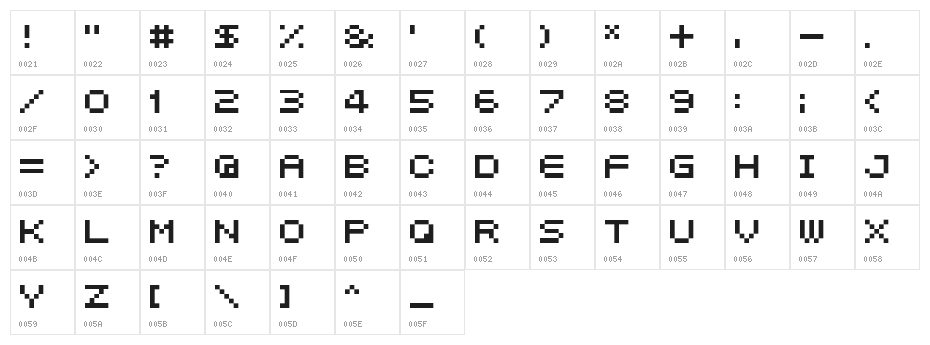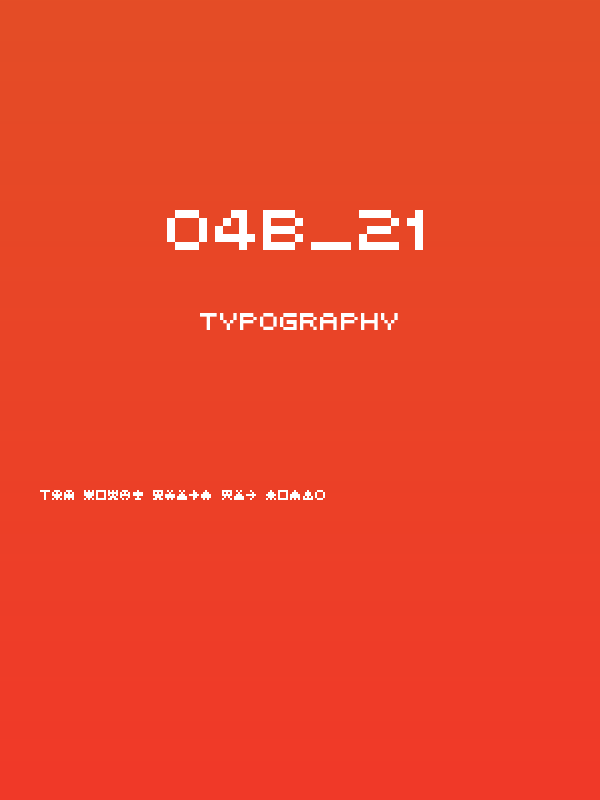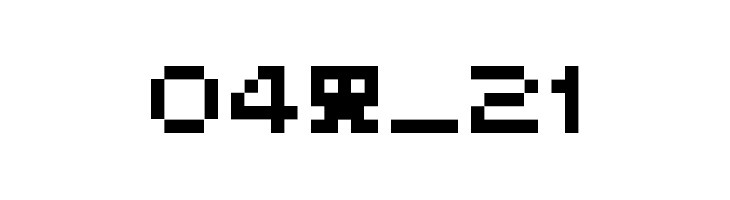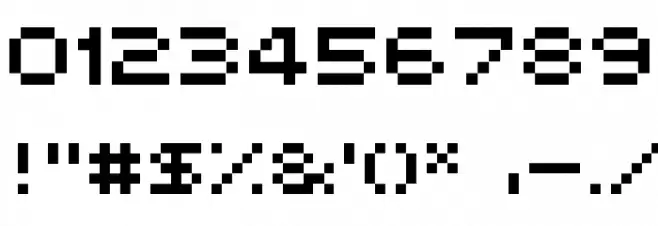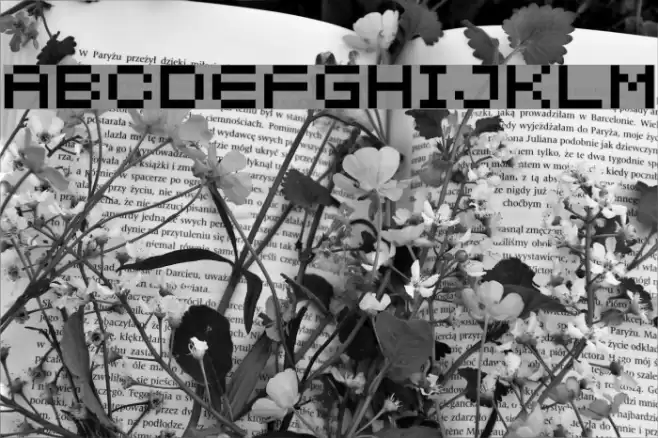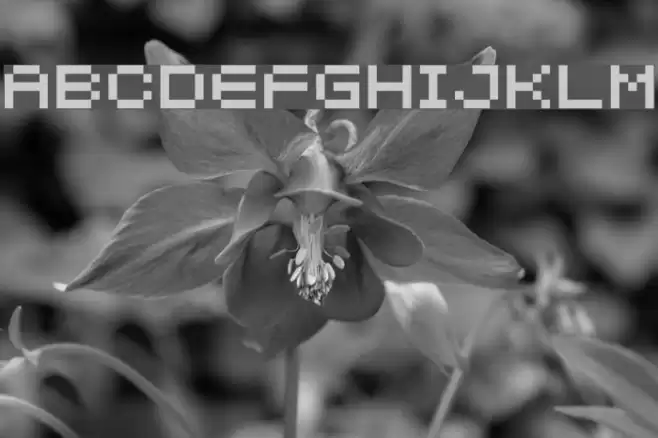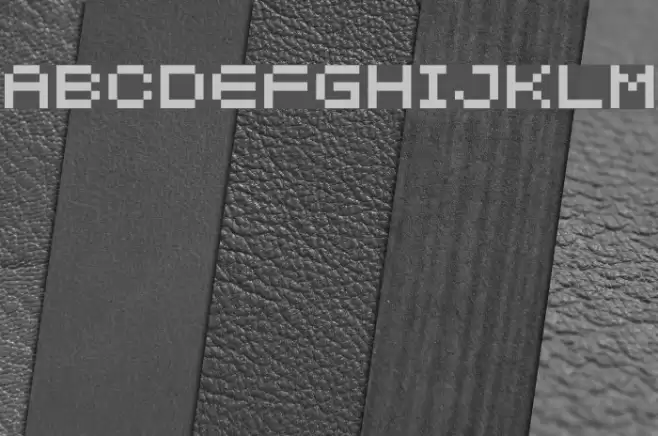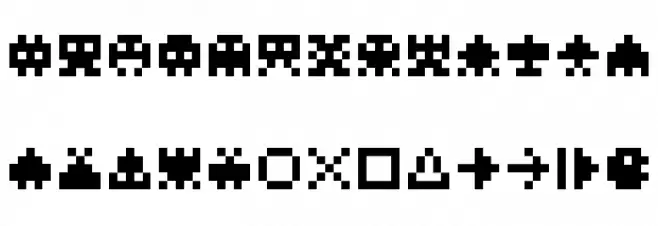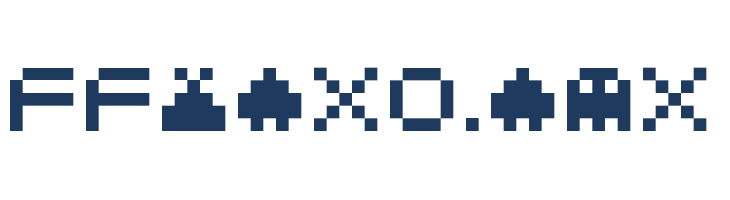
04b_21 Font
| Stil general | Retro, Digital |
| Caz de utilizare | Digital displays, Coding, Retro games |
| Proiecte propuse | Ideal for retro video games, digital art projects, coding environments, and any design requiring a vintage digital look. |